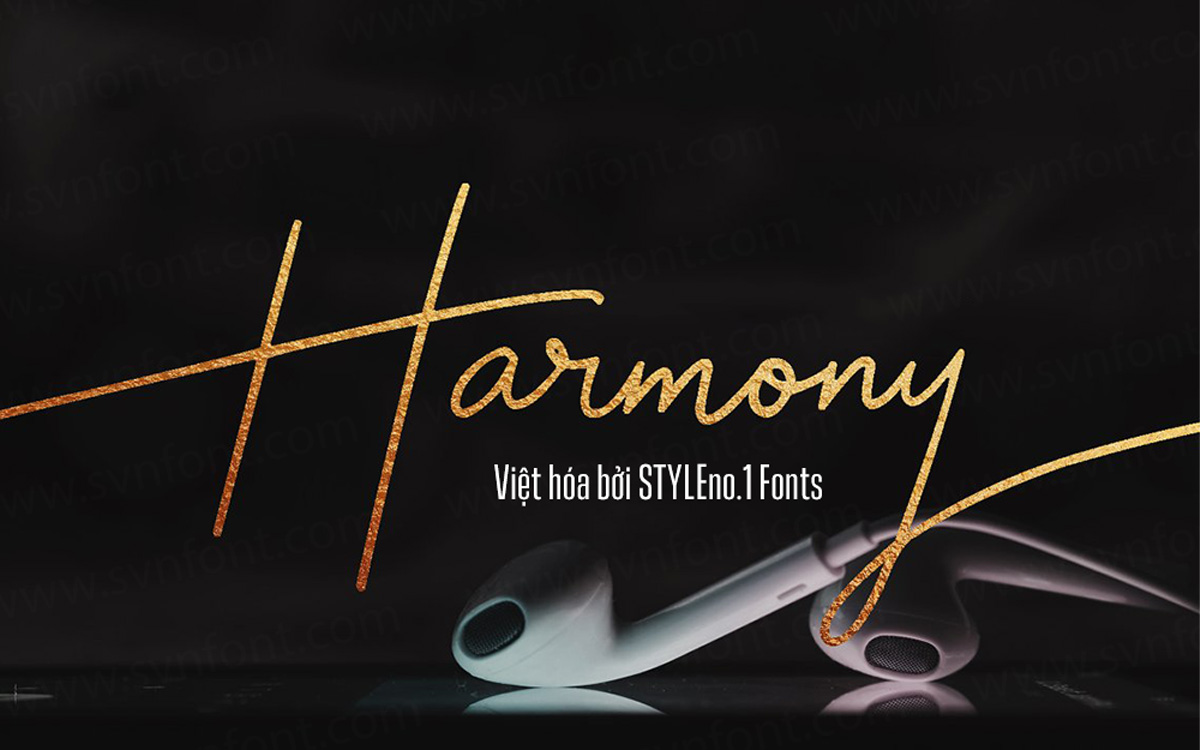
Font chữ viết tay, chữ ký mềm mại cho thiệp cưới, đám cưới SVN-Harmony là sự lựa chọn hoàn hảo dành cho các nhà thiết kế đang tìm kiếm sự tinh tế, sang trọng và lãng mạn trong từng nét chữ. Với các đường nét uốn lượn tự nhiên giống như chữ viết tay thủ công, bộ font này giúp nâng tầm ấn tượng thị giác cho thiệp cưới, phông nền sự kiện và các sản phẩm truyền thông thương hiệu cao cấp. Sự kết hợp giữa tính nghệ thuật vượt thời gian và bản Việt hóa chỉn chu giúp SVN-Harmony trở thành công cụ không thể thiếu trong bộ sưu tập typography của mọi designer chuyên nghiệp.
Font Chữ Viết Tay, Chữ Ký Mềm Mại Cho Thiệp Cưới, Đám Cưới SVN-Harmony – Giải Pháp Thiết Kế Lãng Mạn Và Sang Trọng
Trong thiết kế thiệp cưới và trang trí không gian đám cưới, font chữ đóng vai trò linh hồn giúp thể hiện phong cách cũng như câu chuyện tình yêu của cặp đôi. Một font chữ đẹp không chỉ truyền tải thông tin mà còn khơi gợi cảm xúc lãng mạn, sự trân trọng gửi tới từng vị khách mời. Font chữ viết tay, chữ ký mềm mại SVN-Harmony ra đời để đáp ứng hoàn hảo nhu cầu đó, mang đến nét đẹp nét chữ nết người vừa bay bổng vừa hiện đại.
1. Đường Nét Viết Tay Uyển Chuyển, Mang Đậm Dấu Ấn Chữ Ký Nghệ Thuật
Thành công của font chữ SVN-Harmony nằm ở khả năng mô phỏng chân thực từng nét bút của nghệ nhân thư pháp. Font sở hữu cấu trúc nét chữ mảnh mai, phóng khoáng cùng những đường uốn lượn mềm mại, nhịp nhàng. Khi gõ các ký tự, các nét nối tự nhiên tạo cảm giác như được viết tay thủ công một cách cẩn thận và tràn đầy tâm huyết.
Đặc biệt, phong cách chữ ký (signature style) của SVN-Harmony giúp tên của cô dâu và chú rể trở nên thật sự nổi bật. Điểm nhấn này mang đến vẻ đẹp độc bản, khẳng định gu thẩm mỹ tinh tế và đẳng cấp của chủ nhân buổi tiệc.
2. Tối Ưu Tối Đa Cho Thiết Kế Thiệp Cưới, Menu Và Phông Nền Đám Cưới
Được nghiên cứu và sáng tạo dành riêng cho ngành thiết kế sự kiện và tiệc cưới, font chữ đám cưới SVN-Harmony thể hiện tính ứng dụng vô cùng đa dạng. Bạn có thể dễ dàng phối hợp font chữ này trên nhiều ấn phẩm cưới khác nhau:
- Thiệp mời đám cưới (Wedding Invitations): Tạo ấn tượng sâu sắc cho tiêu đề “Save the Date”, tên cô dâu chú rể hoặc lời mời trang trọng.
- Bảng chào mừng (Wedding Welcome Board): Đặt tại cổng đón khách, mang lại vẻ đẹp ấm cúng, thanh lịch cho toàn bộ không gian tiệc cưới.
- Thực đơn tiệc cưới (Wedding Menu): Thể hiện sự chỉn chu đến từng chi tiết nhỏ nhất trên bàn tiệc dành cho thực khách.
- Thẻ tên bàn và Thẻ cảm ơn (Place Cards & Thank You Cards): Gửi gắm lời cảm ơn chân thành đến người thân, bạn bè qua những nét chữ mềm mại.
- Phông nền sân khấu (Wedding Backdrop): Nét chữ phóng khoáng giúp phông nền chụp ảnh kỷ niệm trở nên vô cùng ăn ảnh và thu hút mọi ánh nhìn.
3. Bộ Ký Tự Việt Hóa Chuẩn Xác, Không Lỗi Dấu Tiếng Việt
Một rào cản lớn khi sử dụng các font chữ viết tay nghệ thuật quốc tế là lỗi hiển thị dấu tiếng Việt. Với bản SVN-Harmony đã được Việt hóa chỉn chu, nhà thiết kế hoàn toàn có thể yên tâm sáng tạo mà không gặp bất kỳ trở ngại nào về mặt kỹ thuật.
4. Khả Năng Ứng Dụng Đa Dạng Từ Thiết Kế Thương Hiệu Đến Mạng Xã Hội
Không chỉ bó hẹp trong phạm vi sự kiện đám cưới, font chữ viết tay mềm mại SVN-Harmony còn là trợ thủ đắc lực cho các dự án nhận diện thương hiệu mang phong cách nữ tính, cao cấp. Các thương hiệu thời trang, spa, mỹ phẩm, tiệm hoa tươi hay nhiếp ảnh gia đều có thể khai thác vẻ đẹp độc đáo của kiểu chữ này.
SVN-Harmony rất phù hợp để tạo logo chữ ký (Signature Logo), đóng dấu bản quyền hình ảnh (Watermark), thiết kế bao bì sản phẩm sang trọng, tạo ảnh trích dẫn nghệ thuật (Quotes) trên Facebook, Instagram hay làm tiêu đề bìa tạp chí phong cách lifestyle.
5. Khả Năng Kết Hợp Font Chữ (Font Pairing) Đa Dạng Và Hài Hòa
Trong thiết kế đồ họa, sự kết hợp giữa các kiểu font chữ khác nhau quyết định tính cân bằng và độ dễ đọc của bản vẽ. SVN-Harmony đóng vai trò là một font chữ trang trí (Display Font) hoặc font tiêu đề xuất sắc, có khả năng bắt cặp hoàn hảo với nhiều dòng font khác:
- Kết hợp với Font Sans-Serif (Chữ không chân): Mang lại vẻ đẹp hiện đại, tối giản và thanh lịch, giúp bản thiết kế vừa trẻ trung vừa có điểm nhấn lãng mạn.
- Kết hợp với Font Serif (Chữ có chân cổ điển): Tạo nên phong cách hoàng gia, hoài cổ và vô cùng quý phái, phù hợp cho các buổi tiệc cưới sang trọng theo phong cách cổ điển.
Bí Quyết Sử Dụng Font SVN-Harmony Đạt Hiệu Quả Thẩm Mỹ Tối Đa
Để phát huy tối đa vẻ đẹp của font chữ ký mềm mại SVN-Harmony trong các sản phẩm thực tế, bạn có thể áp dụng một số kinh nghiệm thiết kế sau:
- Sử dụng đúng mục đích: Hãy dùng SVN-Harmony cho các tiêu đề chính, tên nhân vật hoặc các cụm từ ngắn cần tạo điểm nhấn. Tránh dùng font chữ nghệ thuật này cho các đoạn văn bản dài (body text) để đảm bảo tính dễ đọc.